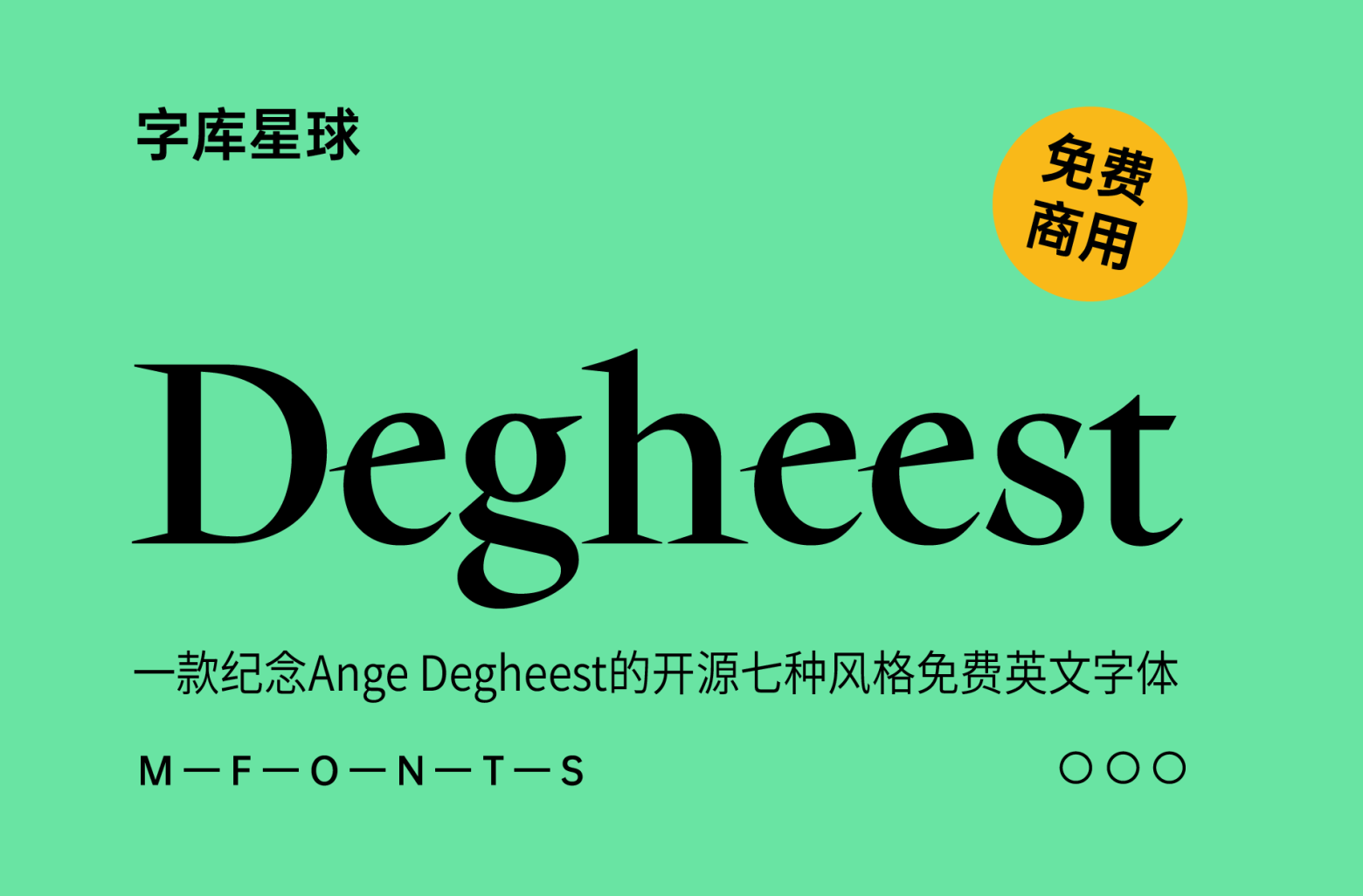
Degheest
Degheest字体家族是一款纪念Ange Degheest的开源7种风格免费英文字体。
在雷恩美术学院发现Ange Degheest的档案后,我们决定举办一场展览,试图最终给予这位设计师她应得的充分认可。在这次展览中,参观者了解了Degheest的生活故事和职业成就,并发现了许多以前从未向公众展示过的原始档案文件。除了这项历史研究,我们还恢复了Ange Degheest的一些最引人注目的字体和刻字作品,这些作品现在可以在Velvetyne Type Foundry的网站上以开源许可的数字格式提供。
复活意味着:复活、重新激活、更新;在很多方面,我们的工作都是一种复活。我们确实不得不通过翻阅Ange Degheest的档案,挖掘一个经历了许多时代和地点的女人的故事,来重新唤起对她的记忆。只有当我们很好地了解了她的生活故事,我们才能恢复她的字体。复兴她的设计并免费广泛分发,是我们纪念Ange Degheest并在21世纪赋予其新生命的方式。
Deheest是Ange Degheest、Eugénie Bidaut、Oriane Charvieux、Mandy Elbé、Luna Delabre、Camille Depalle、Justine Herbel、May Jolivet和Benjamin Gomez在雷恩EESAB印刷工作室创作的一个项目。
Abordage
Basalte
Director
Equateur
FT88
Latitude
Louise